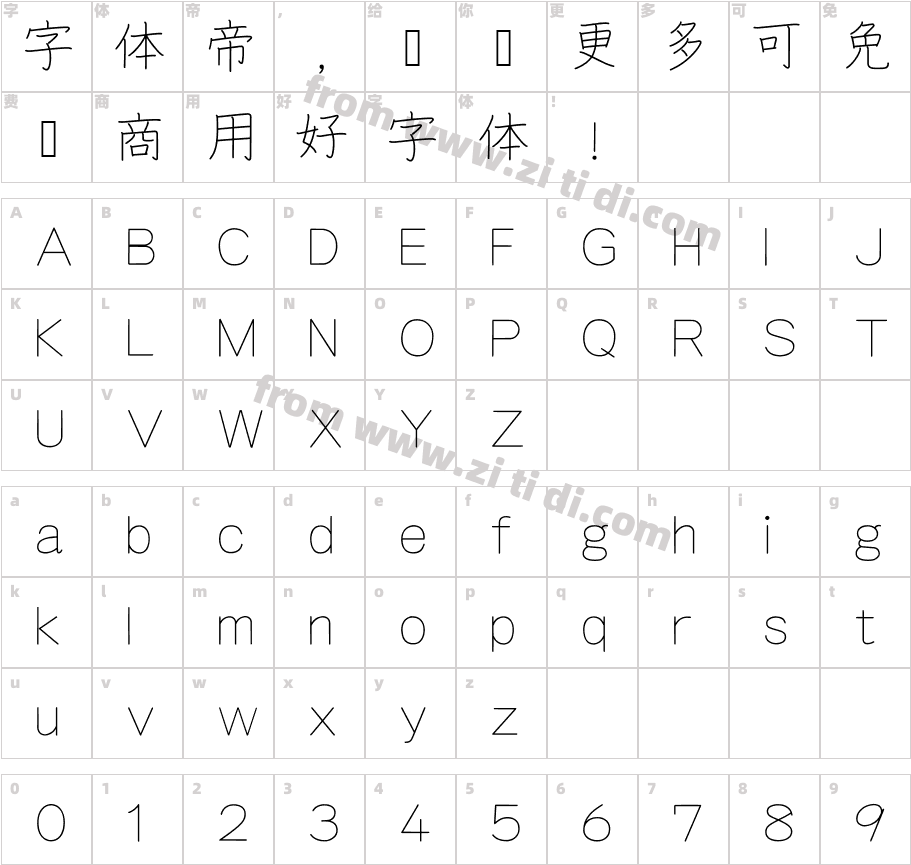
澄明手写体是一种非严肃的汉字字体,有近7700个字形,出于兴趣而创造。我把这个字体放出给有需要的人使用。我创造了日本汉字和其他一些汉字从汉字,并保留笔画顺序字体。
我以日本作家Kamo no Choumei(1155-1216)的名字命名这种字体,写了《十平方英尺小屋的生活》。
“澄明手写体Choumei”是一款书写很新颖的字体,字体大方,适合各种设计作品使用!欢迎下载!